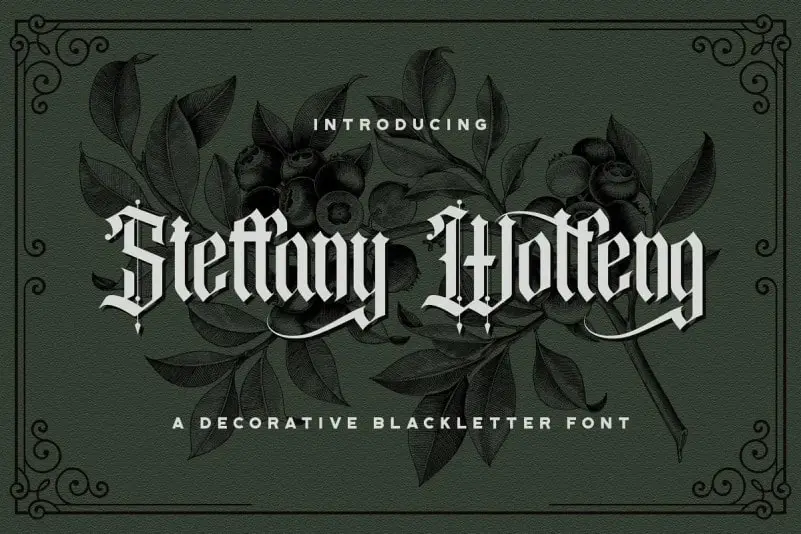
Steffany Wolfeng Display Font – Download Grátis
A Steffany Wolfeng Font é uma nova tipografia criada pela StringLabs com uma combinação de caracteres elegantes e vintage que transbordam classe. Seu design foi meticulosamente planejado para oferecer um caráter único, combinando letras maiúsculas e minúsculas de maneira perfeita, além de incorporar alternativas únicas. Essa fonte é perfeita para aplicação em projetos gothicos, como estampas, roupas, embalagens, identidades corporativas ou qualquer outra iniciativa relacionada a estilos góticos. Com seu ar elegante e vintage, essa fonte vai tornar seus designs de um jeito único e chamativo.